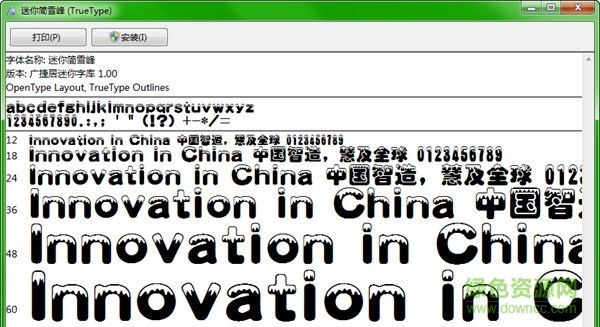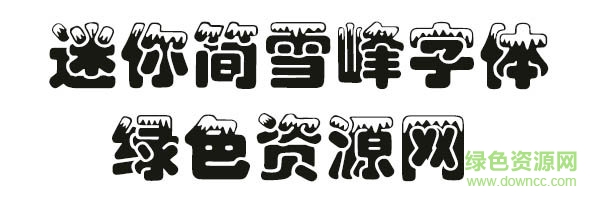
迷你簡雪峰是一款應用于廣告創(chuàng)意設計方面的簡體中文字體,該字體每一個字都是以白雪打頭,黑白分明,整體效果非常出色,且字庫完整,可以適用于名片設計、平面設計、廣告設計、報紙雜志、企業(yè)LOGO、商標注冊、電視臺廣告等領域,有喜歡的網友可免費下載收藏。
柔滑細膩,強壯有力,清晰醒目,美麗可愛等。字體的創(chuàng)造過程相當艱辛,迷你簡雪峰字體給人的美感也是難以言表的。